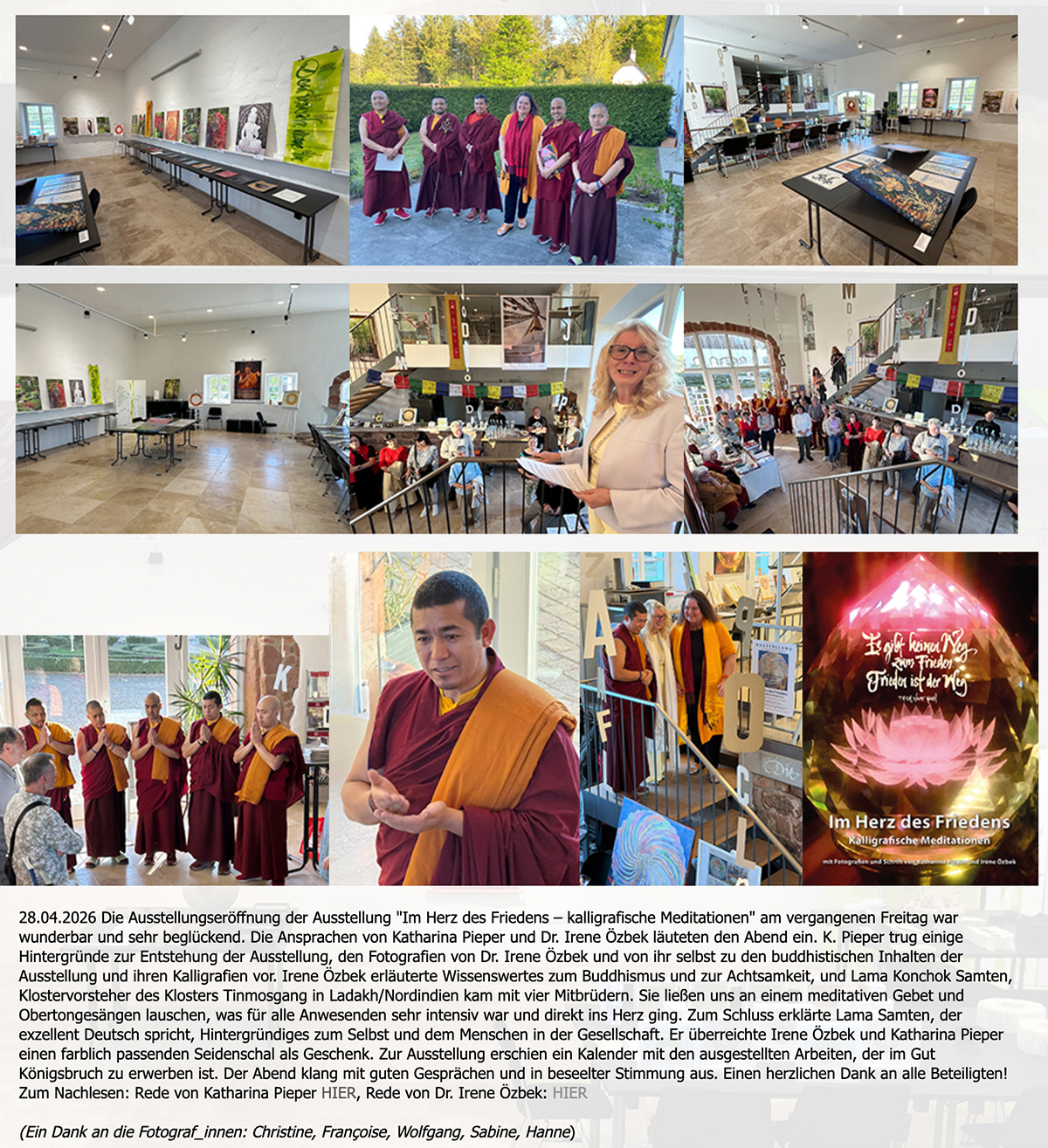
In den letzten Tagen waren in der Saarbrücker Zeitung in mehreren Regionalausgaben
dieser Zeitungsartikel
zu lesen. Ich freue mich darüber!
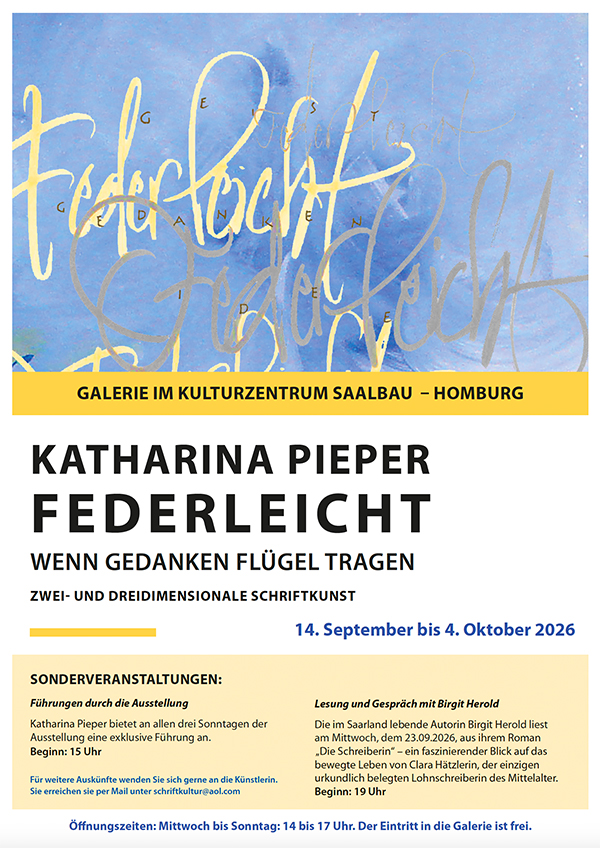
Am 14. September um 18.30 Uhr wird meine Ausstellung
FEDERLEICHT – WENN GEDANKEN FLÜGEL TRAGEN
in der Galerie im Kulturzentrum Saalbau in Homburg eröffnet.
Begrüßung: Raimund Konrad (Beigeordneter für Kultur und Tourismus)
Einführung: Dr. Françoise J. Mathis-Sandmaier M.A. (Kuratorin)
An allen drei Sonntagen biete ich der Ausstellung eine exklusive Führung an.
Lesung und Gespräch mit Birgit Herold:
Die im Saarland lebende Autorin Birgit Herold liest am Mittwoch, dem 23.09.2026,
aus ihrem Roman „Die Schreiberin“ – ein faszinierender Blick auf das bewegte Leben
von Clara Hätzlerin, der einzigen urkundlich belegten Lohnschreiberin des Mittelalters.
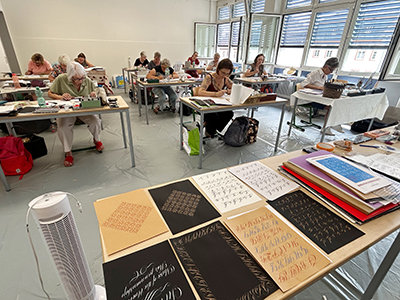
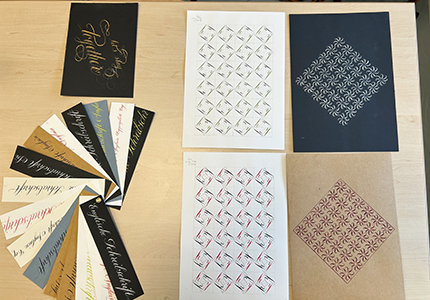
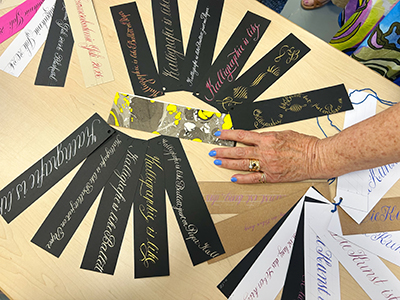
| Die Saarländische Sommerakademie in Blieskastel, organisiert von der Freien Kunstschule Artefix in Homburg, ging soeben zu Ende. Die Teilnehmerinnen kamen wieder aus ganz Deutschland und aus Luxemburg. Das diesjährige Thema war die elegante englische Schreibschrift. Bei guter, ja familiärer Stimmung, widmeten sich 12 enthusiastische Kalligräfinnen eine Woche lang Kleinbuchstaben, Großbuchstaben, Blattgestaltung, verschiedenen Schriftgrößen, Schwüngen und Schleifen, Übungen mit Einzelbuchstaben und kalligrafischen Kreisen. Es war eine schöne und intensive Woche, und die Hitze ließ uns, wie in jedem Jahr, nicht im Stich! Bei Außentemperaturen bis 36 Grad klebte das ein oder andere Mal der Arm am Papier fest, die Gouache trocknete zu schnell oder der Kreislauf machte auch mal schlapp. Ein Abend in Jägersburg im Biergarten am Weiher war eine willkommene Abkühlung. Wir freuen uns schon auf 2027, wenn das Thema "Prägung" lautet. |
Auch in der Homburger Stadtzeitschrift "Es Heftche" erschien ein wunderbarer Artikel über mein Wirken am Gut Königsbruch
und unsere laufende Ausstellung "Im Herz des Friedens – kalligrafische Meditationen" (von Katharina Pieper und Irene Özbek).
Der Autor des Artikels, Chris Ehrlich, hat die Kalligrafie als solche und den "Geist", der in den Räumen
der Stiftung Schriftkultur schwebt, aufs vortrefflichste beschrieben!
In der Stadtzeitschrift BAGATELLE in Homburg erschien der Bericht von Chris Ehrlich ebenfalls in diesen Tagen.
Heute ist in der Saarbrücker Zeitung ein schöner Artikel über die Ausstellung
"Im Herz des Friedens – kalligrafische Meditationen"
Einen Tag nach der Ausstellungseröffnung im Saarparkcenter Neunkirchen: Die Mönche aus Ladakh gestalteten über mehrere Tage ein Sandmandala.
An diesem Tag wurde es in einer rituellen Zeremonie wieder aufgelöst. Ich übergab Lama Konchok Samen einen Umschlag mit einem größeren Beitrag
zur Errichtung des Waisenhauses, das an das Kloster in Tinmosgang angegliedert ist. Die Hälfte der Einnahmen aus dem Verkauf des Kalenders
Heute ist der internationale Tag der Handschrift. Ich habe einen Brief an die Mitglieder
der Stiftung Schriftkultur e. V. geschrieben, den ich an dieser Stelle gerne zur Verfügung stellen möchte.
Er enthält auch eine Buchempfehlung zum abgebildeten Buch "Wer nicht schreibt, bleibt dumm".
Fotos: links die kalligrafische Arbeit (Acryl und Gouache auf Leinwand, 40 x 120 cm), rechts Birgit Herold, K.P. und Birgit Herolds Mann,
die extra zur Ausstellungseröffnung gekommen sind.
„Hommage an die mittelalterliche Schreiberin Clara Hätzlerin“In meiner kalligrafischen Arbeit für die Jahresausstellung 2025 der Homburger Künstler, die am 24. November eröffnet wurde und unter dem Thema "ver-rückt" steht, möchte ich auf eine außergewöhnliche Frau aufmerksam machen. Clara Hätzlerin war eine der ganz wenigen Frauen in dieser Zeit, die lesen und schreiben konnte. Sie lernte das Schreiben als Kind von ihrem Vater, der Notar war, und lebte in Augsburg. Sie schrieb in einer Kanzleibastarda, die später von Schriftgelehrten als Referenz gewählt wurde. Ich habe für meine Arbeit diese Schrift erlernt und Textauszüge aus dem historischen Roman „Die Schreiberin“ von Birgit Herold geschrieben. Als Collage sieht man Kopien aus Clara Hätzlerins Liederbuch, das um 1450 entstand und Liebeslyrik enthält. In einer handschriftlich-kalligrafischen Schrift sieht man das Wort „Buchstabenvögel“. Es entstammt ebenfalls Birgit Herolds Buch und beschriebt einen Traum, in dem Clara von vom Himmel fallenden Buchstaben träumt. Diese Buchstaben sieht man links in Rot geschrieben und von oben nach unten „fallen“. Es handelt sich um die mittelalterliche Schrift “Textur“, die Johannes Gutenberg, Erfinder der beweglichen Letter und Drucker der „Gutenberg-Bibeln“, für seine Schriftwerke verwendet hat und in dessen Werkstatt in Mainz Clara im Roman auch als Schreiberin tätig war. Es ist die Lebensgeschichte einer „verrückten“ Frau, die in ihrer Zeit einzigartig war und deren Schriftstücke und Bücher bis heute studiert werden. Das Buch von Birgit Herold hat mich so begeistert, dass ich mich diesem Thema gewidmet habe. Die Kuratorin der Ausstellung, Dr. Françoise Mathis-Sandmaier, trug in nicht geringem Maße zur Entstehung dieser kalligrafischen Arbeit bei. |
Im Bildungszentrum der Arbeitskammer Kirkel wurde am 19. November die Ausstellung 5 ARTen eröffnet.
Es wird der Nachfolger des kalligrafischen Kochbuchs, das ebenfalls in der Sommerakademie entstand (2015). Am Ende des Kurses wurden viele frisch geschriebene Rezepte
auf den Tischen in der Galerie präsentiert. Sie können derzeit in der Galerie der Stiftung Schriftkultur sonntags zu den Öffnungszeiten angesehen werden.
Museum und Galerie sind seit 17. Mai (Internationaler Museumstag) wieder geöffnet. Am erste Tag kamen viele Interessierte und Mitglieder,